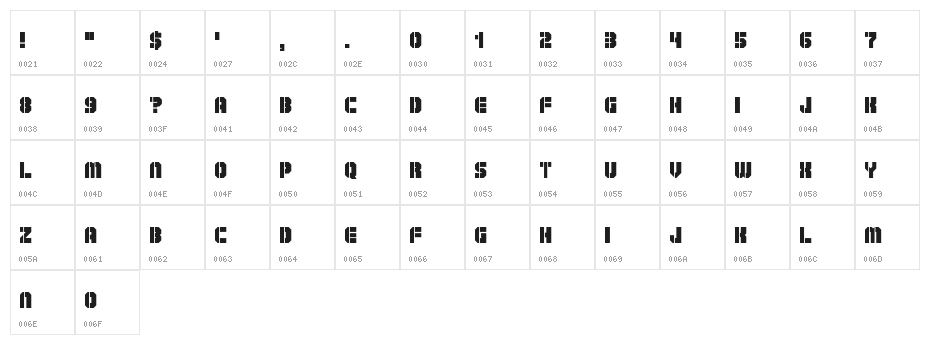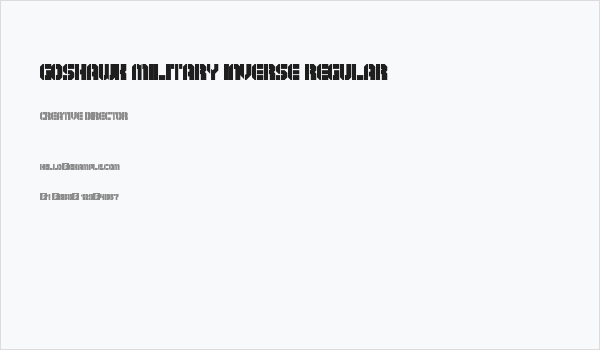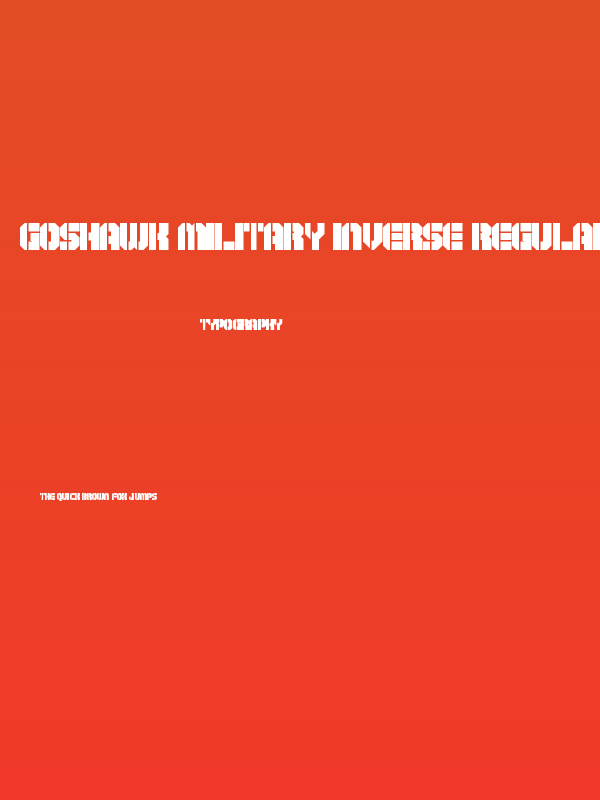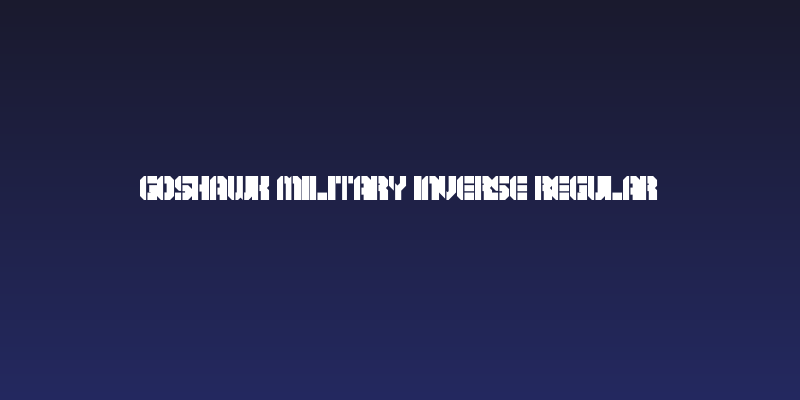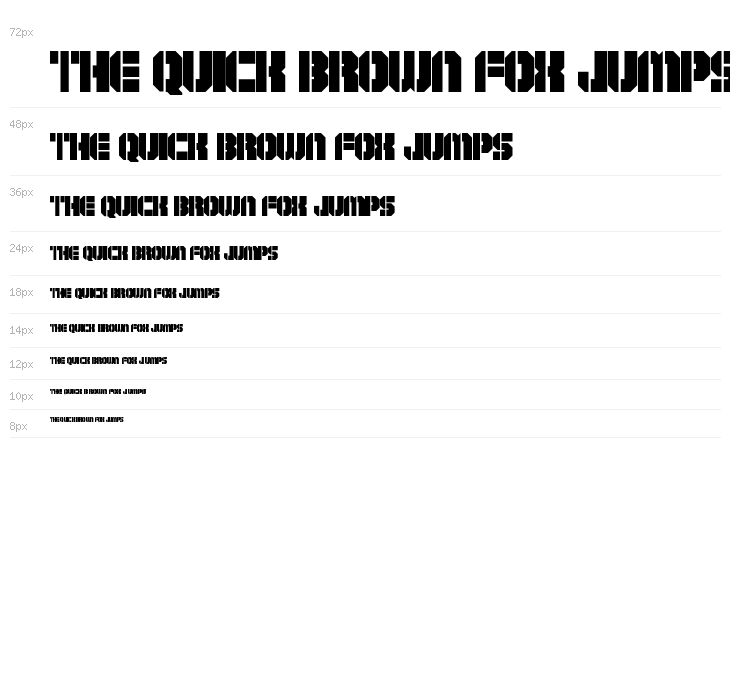
Goshawk Military Inverse Regular Font
| Proyectos propuestos | Ideal for military-themed posters, video game graphics, branding for tactical gear, or any project needing a strong, authoritative look. |